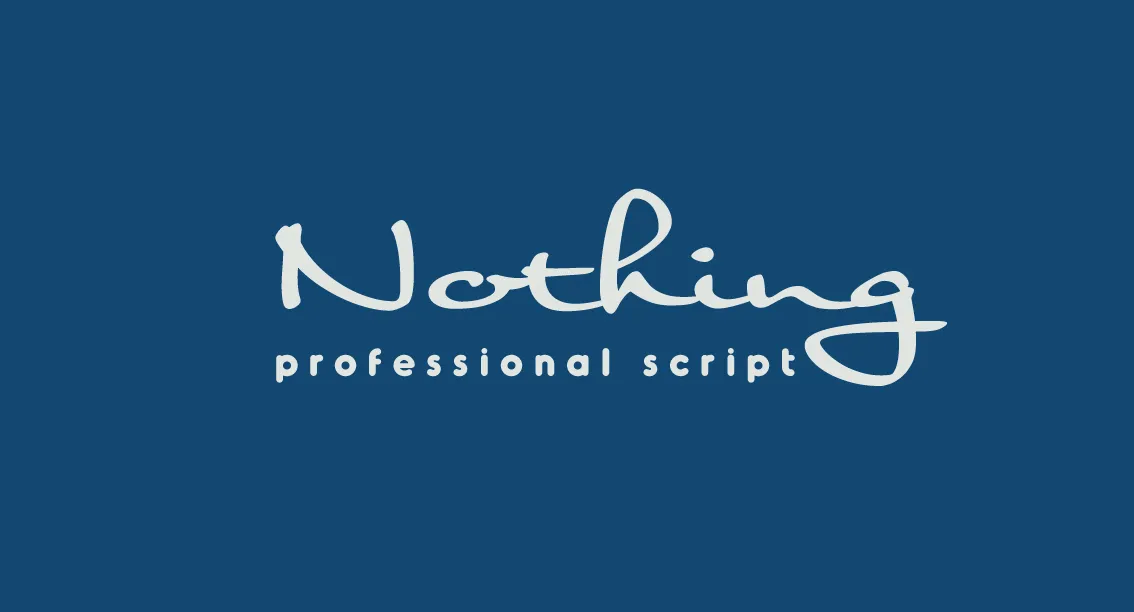
Nothing Font – Fonte Grátis
Nothing Font
A Nothing Font é uma fonte à mão livre criada pelo designer Hamilton. Suas linhas espessas e delicadas capturam a essência do estilo manuscrito, oferecendo aos designers uma ferramenta poderosa para criar designs únicos e autênticos. Com seus traços suaves e sua capacidade de se adaptar facilmente a várias aplicações, esta fonte é perfeita para quem busca uma opção versátil que seja tanto funcional quanto bela. Adotada por designers do mundo inteiro, Nothing Font foi criada com o intuito de tornar recursos gráficos de alta qualidade mais acessíveis. O designer Hamilton enriqueceu a experiência de uso dessa fonte à mão livre oferecendo-lhe um tom elegante e sofisticado que é perfeito para uma variedade de projetos. Seja você um profissional ou um amante da design, Nothing Font certamente será o elemento adicional que seu próximo projeto precisa.